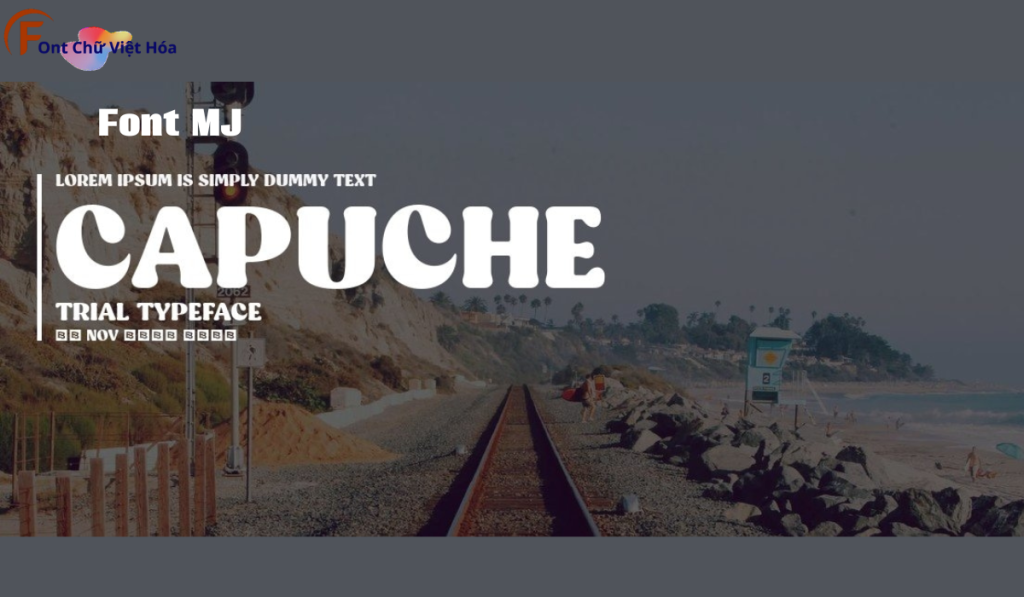
Font MJ Capuche Black Việt Hóa
Tác giả: MJ
Bộ Font: MJ
Độ dày: Black
Font MJ Capuche Black Việt Hóa là một font chữ không chân mạnh mẽ, thuộc bộ font MJ. Được thiết kế với mục tiêu mang lại sự nổi bật và ấn tượng, font này lý tưởng cho các dự án thiết kế như tiêu đề, quảng cáo, và bao bì sản phẩm. Với các nét chữ đậm và chắc chắn, Font MJ Capuche Black Việt Hóa không chỉ dễ đọc mà còn tạo cảm giác mạnh mẽ và quyết đoán. Việc Việt hóa font giúp người dùng dễ dàng sử dụng trong các thiết kế tiếng Việt, mang lại sự tiện lợi và thẩm mỹ cao.